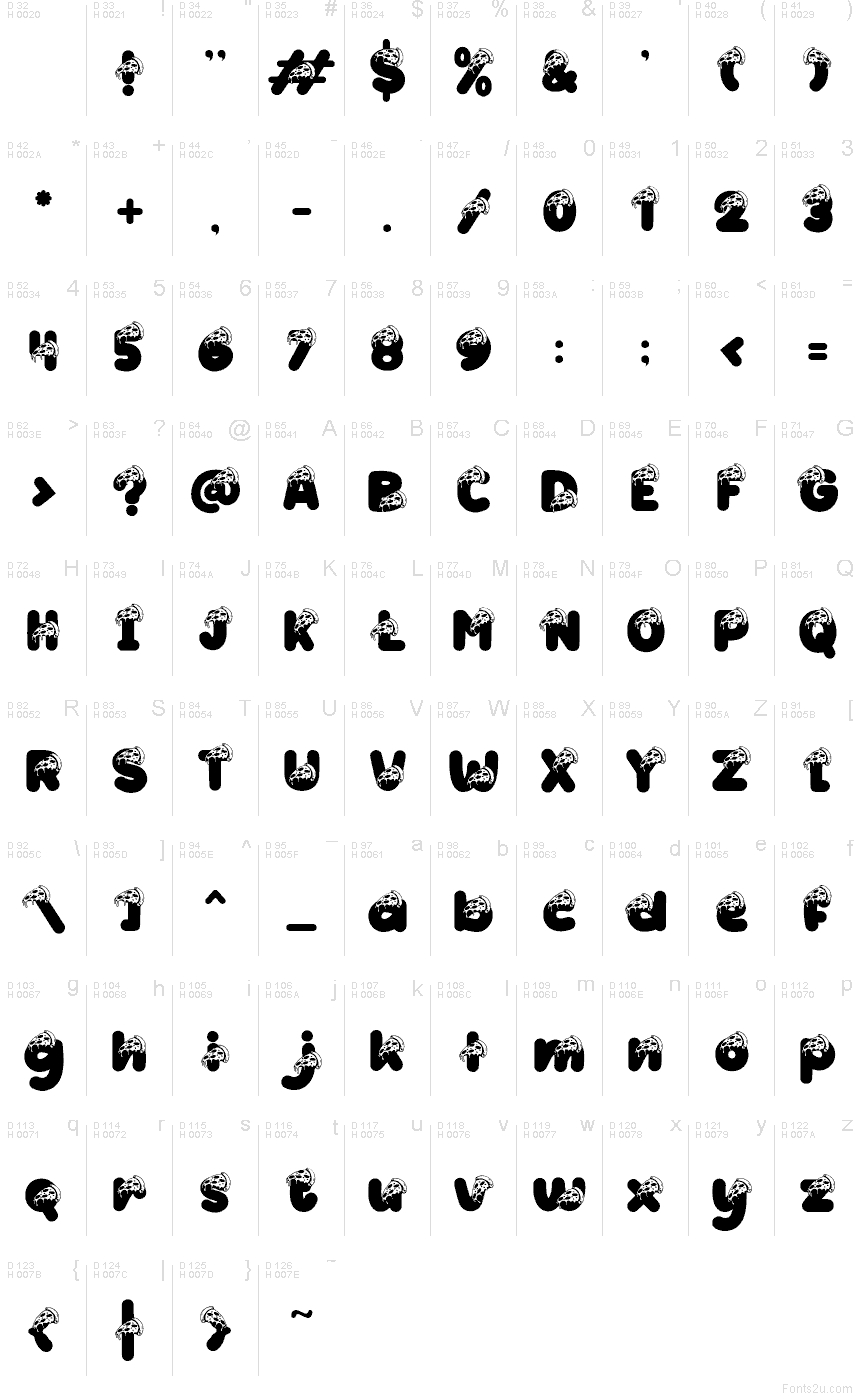
Smoky Maple Six od Putracetol Studio to darmowy font displayowy z efektem rozpuszczania, idealny do projektów związanych z jedzeniem – zabawny, kreskówkowy i z charakterem. Litery są pękate i miękkie, zwieńczone „kapiącymi” kształtami, co nadaje całości lepkiego, niechlujnego i nieco absurdalnego wyrazu, przypominającego bardziej maskotkę przekąski niż standardowy krój ozdobny.
Naturalnie pasuje do opakowań słodyczy lub fast foodów, menu na tablicach w kawiarniach, zaproszeń na przyjęcia dla dzieci, miniaturek na YouTube oraz nagłówków plakatów, gdzie darmowy font z taką teksturą działa błyskawicznie. Ponieważ motyw polewy powtarza się na literach, świetnie sprawdza się również w krótkich nazwach, logotypach i hasłach reklamowych, które potrzebują „smakowitego” klimatu.